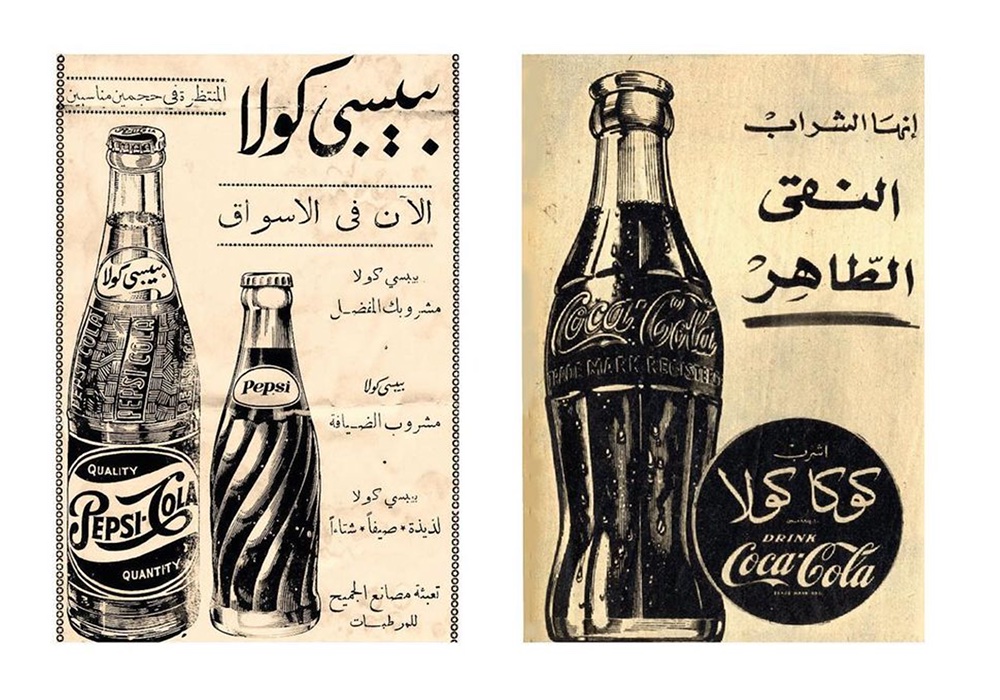
«Type Platform, espacio de investigación de tipografías no latinas» por Ana Moliz
Type Platform es una plataforma de diálogo, reflexión y debates alrededor de alfabetos infrarrepresentados en el mundo tipográfico que se centrará en la tipografía árabe
Cuando hablamos de historia de la tipografía o nos acercamos a la tipografía como disciplina académica desde esta parte del mundo lo hacemos generalmente con la mente puesta en el alfabeto latino, el alfabeto mayoritario en Occidente. También nos resulta familiar que muchas fuentes tipográficas presenten, además del latino, el alfabeto hebreo, el cirílico y el griego.
Pero no podemos olvidar que existen otros alfabetos, otros muchos alfabetos y sistemas de escritura con muy poca representación en el ámbito de la tipografía, no ya digital, sino en general. Más de la mitad de los usuarios de internet usan alfabetos no latinos.
espacio de investigación
Type Platform nace con la intención de erigirse en un espacio de conocimiento, reflexión e investigación tipográfica alrededor de estos sistemas de escritura infrarrepresentados, aunque focalizando su espacio de investigación principalmente en el árabe.
tipografía árabe
Como se declara en la página web del proyecto, la tipografía árabe lleva siglos de retraso con respecto al ámbito de la tipografía latina. Un parco desarrollo que se hizo si cabe más patente con la eclosión de la tecnología digital y su impacto en la tipografía.
Pero en los últimos años se ha producido un considerable empuje en la producción tipográfica árabe que ha traído consigo la necesidad de generar espacios de discusión y reflexión que amplíen y consoliden las bases de la disciplina.
Por lo tanto Type Platform nace con la vocación de erigirse en la plataforma que dé voz a cuantos profesionales de la tipografía, diseñadores y docentes quieran aportar conocimientos y reflexiones sobre el pasado, el presente y el futuro de la tipografía árabe, además de otros alfabetos de mínima presencia tipográfica. Un patrimonio de incalculable valor que bien merece ser preservado.
Es una plataforma para reflexionar sobre el pasado, el presente y el futuro de la tipografía árabe, además de otros alfabetos de mínima presencia tipográfica.
Charlas y debates retransmitidos en directo a través de su canal de Youtube serán la principal vía de difusión de la plataforma, además de ensayos, artículos y, por supuesto, experiencias prácticas de diseño tipográfico.
Hasta la fecha, se puede acceder en Youtube a dos conversaciones. Una, con el diseñador tipográfico iraní Amir Mahdi Moselhi, cuyas investigaciones se centran en sistemas de escritura persas anteriores a la era musulmana, y otra, con la diseñadora gráfica y tipográfica Azza Alameddine, que centra su trabajo en la construcción de identidades visuales en árabe.
Encontramos, además, en su perfil de Instagram, pero todavía no visible en el canal de Youtube (esperemos que pronto lo esté), el anuncio de una charla que tuvo lugar el pasado 5 de diciembre con Gerry Leonidas, profesor de Tipografía en la Universidad de Reading, en Reino Unido, y una de las personalidades académicas más prestigiosas del mundo tipográfico.
Ojalá se consolide el proyecto de Type Platform y dé lugar a un enriquecedor flujo de conocimientos tipográficos.